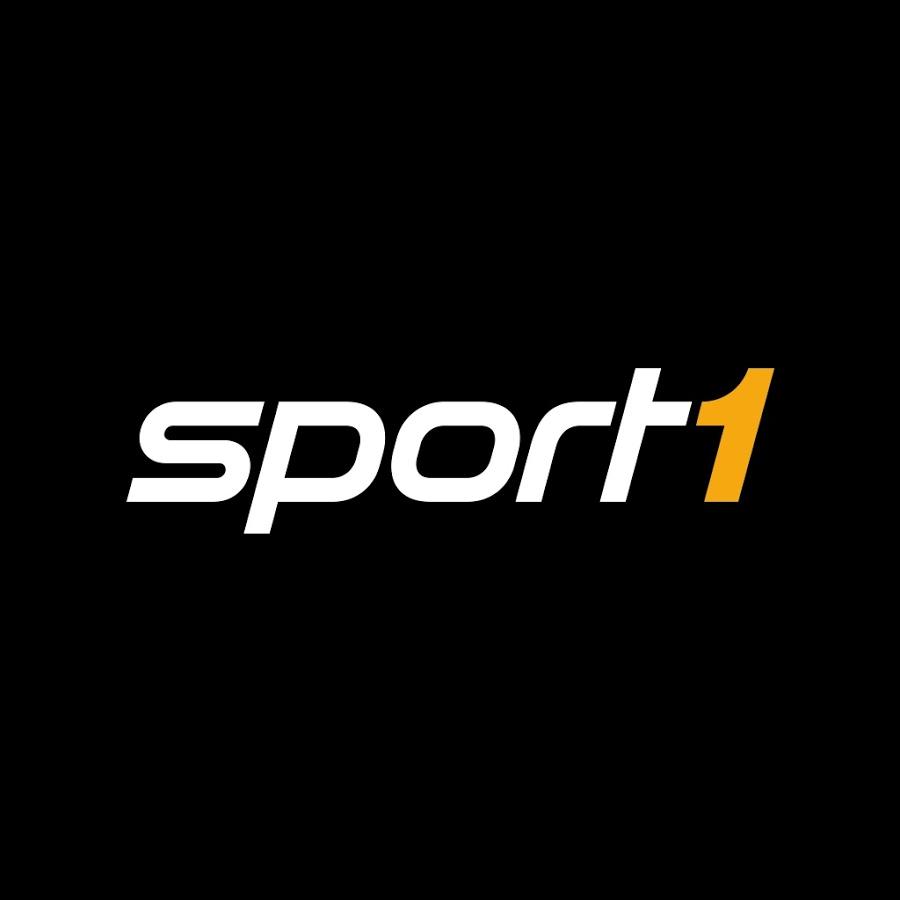
Schriftart Sport1
Nicht zwingend – im Idealfall eher im Gegenteil – wird ein Logo aus einer frei verfügbaren Schriftart gesetzt. Häufig werden die Buchstabenformen neu konstruiert oder Buchstaben einer bestehenden Schriftart werden modifiziert (was oft zweifelhafte Ergebnisse zur Folge hat). In Deinem Fall gibt es zwar viele ähnliche Schriftarten … z.B. die Korataki – ich würde aber davon ausgehen, dass die Buchstaben in dem Logo nicht 1:1 mit einer verfügbaren Schriftart gesetzt wurden.